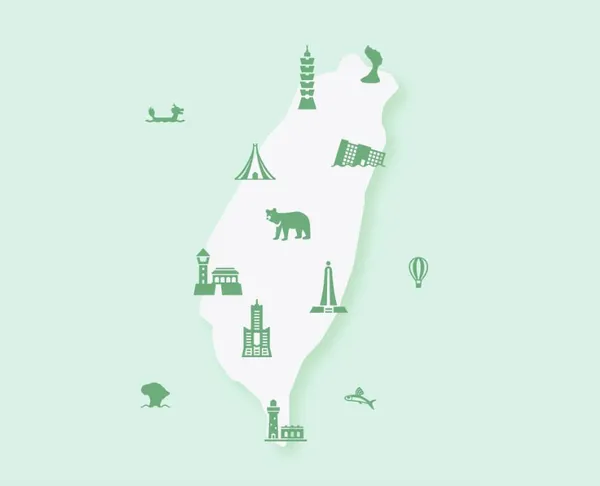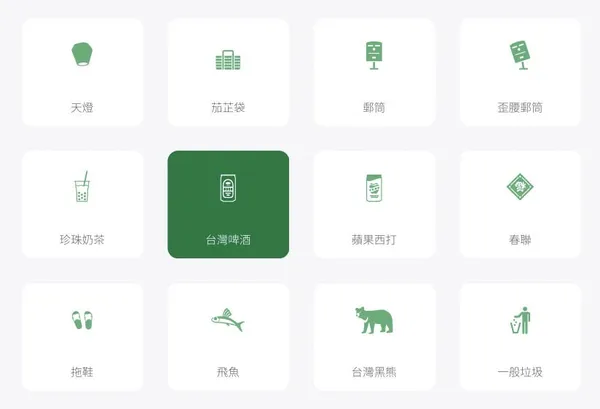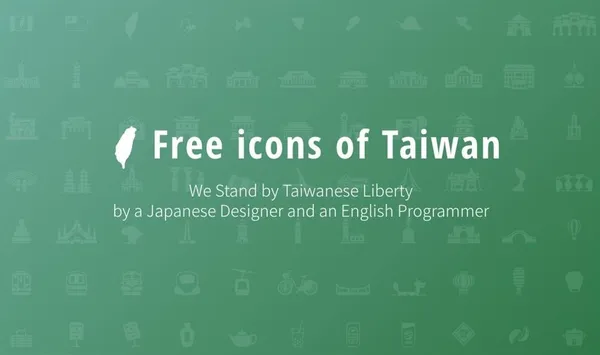
台灣專屬圖標免費下載!日、英設計師聯手打造,珍珠奶茶、茄芷袋都入列
因為喜歡台灣,兩位居住在台灣的設計師:日本人 Holoko 以及英國人 Rob 攜手打造了「Taiwan Icon Font」,第一版以台灣旅遊景點為發想,把眾多台灣景點都畫成圖示字體(icon),免費提供給台灣的旅遊產業,希望在中國限制台灣旅遊的情況下,吸引除了中國以外其他國家的旅人造訪台灣。(點此免費下載)
「我們以台灣獨立運動人士金美齡的口號『STAND BY TAIWAN』為這次計劃的核心概念。我們想跟台灣人說:我們,與台灣站在一塊!」
Holoko 表示,我們支持「台灣」,因為台灣有好大的吸引力。每年,去台灣旅遊的日本人越來越多,甚至在東京,也能見到好多人在喝珍珠奶茶。更重要的是,台灣是我們的朋友,日本人都還沒忘記日本東北大震災時台灣人的捐助。日本首相安倍晋三更稱台灣為好朋友。
Taiwan Icon Font 的第一個版本以「旅遊」為發想。Rob 與 Holoko 進一步表示,當初在得知中國共產黨限制中國人去台灣旅遊,為台灣觀光產業帶來衝擊後,便希望藉由畫下台灣景點,讓台灣的旅遊業者能夠加以應用,除了吸引中國人以外的旅客造訪台灣外,也同時讓他們有機會了解到台灣現下的處境。
在 Taiwan Icon Font 的 100 個圖示中,不僅搜羅了台灣國旗、本島與離島外,更有歷史建築,如故宮、中正紀念堂、台南孔廟等。此外,北中南各地的知名景點也一併囊括,包括:臺中國家歌劇院、野柳女王頭、龍騰斷橋、蘭陽博物館等。而屬於台灣人民的共同記憶:珍珠奶茶、大同電鍋、茄芷袋也入列其中。未來,他們也表示將會持續更新、發表新的圖案!(可以到這個Medium的頁面給他們鼓勵和建議)
Taiwan Icon Font